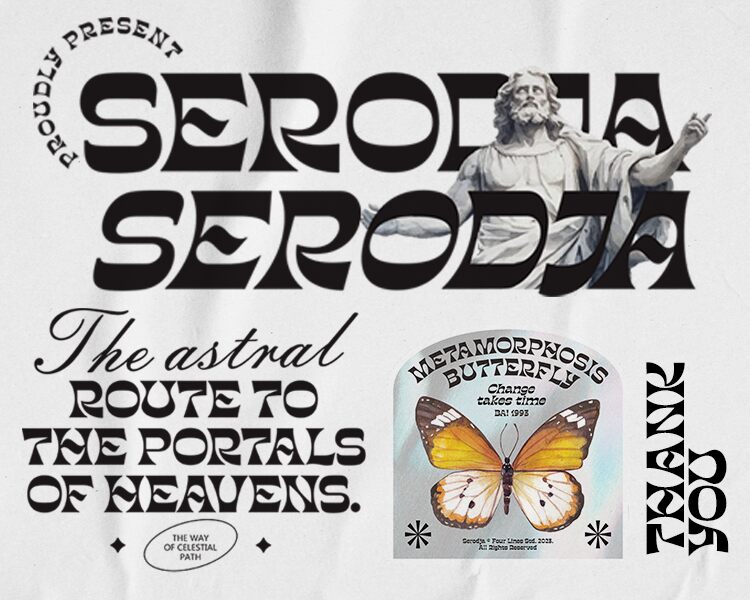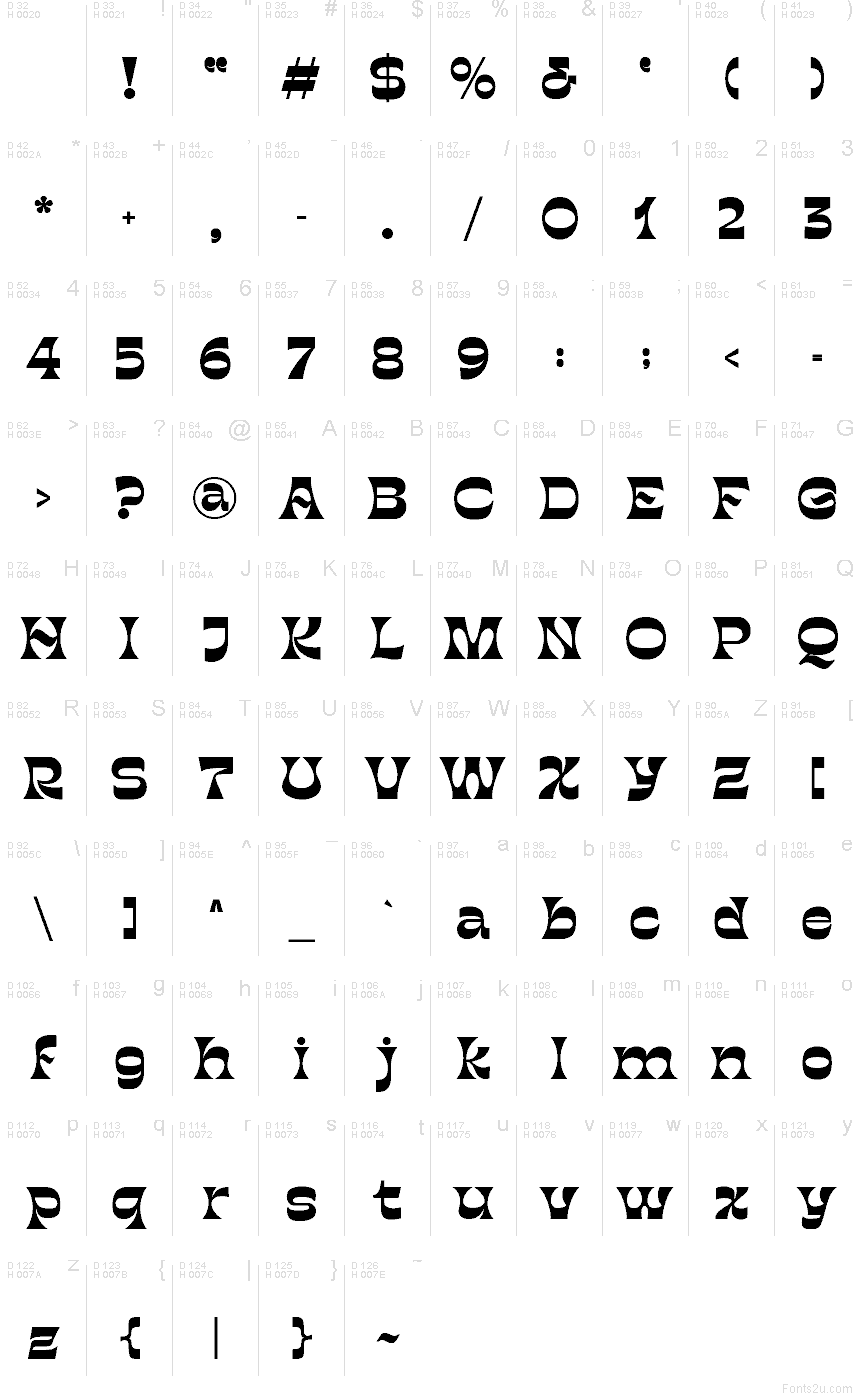
Serodja di Four Lines Std. è un font display gratuito dal gusto retrò, caratterizzato da forme arrotondate a basso contrasto e tagli morbidi e squadrati che richiamano il ritmo tipico degli anni '70. I caratteri appaiono compatti e fluidi, con curve ampie e una geometria essenziale che rendono ogni scritta equilibrata e versatile.
Serodja è perfetta per titoli di poster, cover di album, packaging, branding per caffè e grafiche social in cui è necessario un accento retrò distintivo. Grazie alle sue curve uniformi e ai dettagli curati, questo font gratuito è ideale anche per loghi e brevi testi promozionali, dove garantisce un impatto visivo immediato.
Presentazione e campione visivo del carattere Serodja
Mappa dei caratteri di Serodja
Mappa dei caratteri di Serodja: Latino di base, pagina 1
Glifi del carattere Serodja — Latino di base, pagina 1